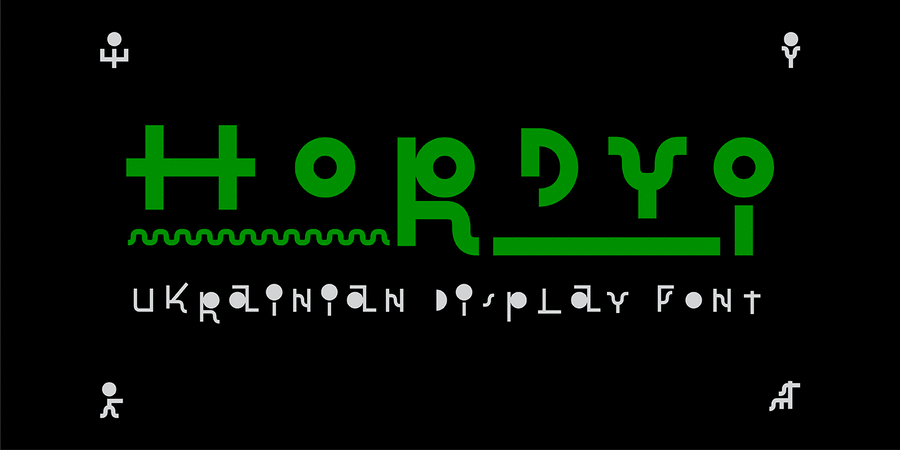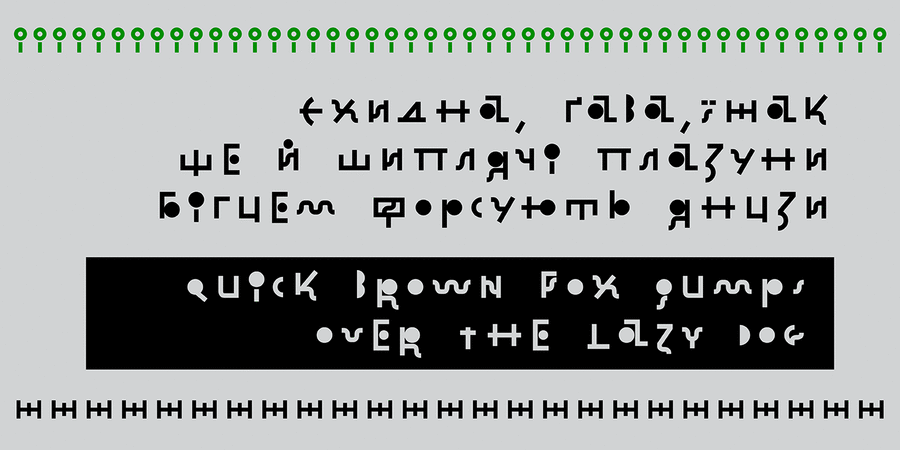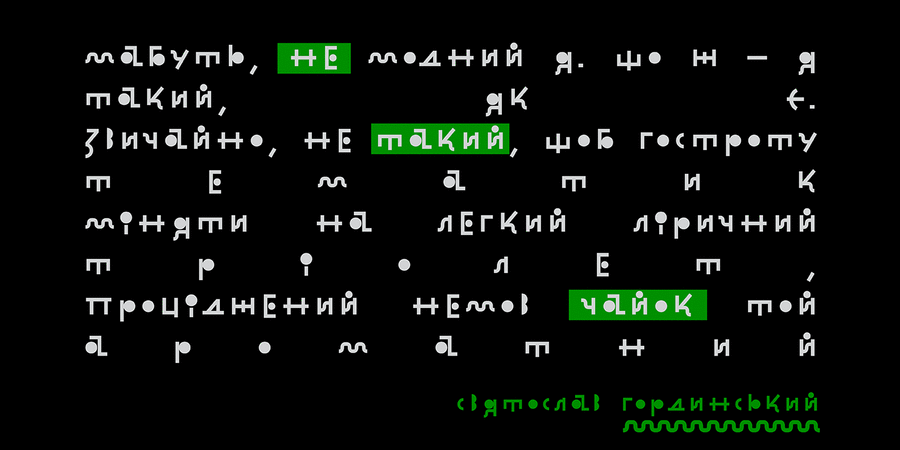
Цей шрифт був створений на основі книжкових обкладинок українського графічного дизайнера Святослава Гординського, який працював у 20-х роках минулого сторіччя. В його роботах простежується вплив німецького конструктивізму, що передано у формах літер і моноширинних штрихах. Шрифт Гордий – це не ревайвал літер Гординського, а сучасне переосмислення натхненне формами комп’ютерного коду 80-х років минулого століття. Форми літер настільки універсальні, що стали основою піктограм (людини, коня та собаки), які становлять систему символів стрілок.
Шрифт Гордий балансує на межі читабельності, що надає йому самодостатнього характеру в дизайні. Комфортно використовувати в мінімалістичних дизайнах постерів, обкладинок книг, логотипах, заголовках, фірмовому стилі, упаковці та інших видах графічної продукції. Шрифт розробила Анна Коваленко у 2023-му році.